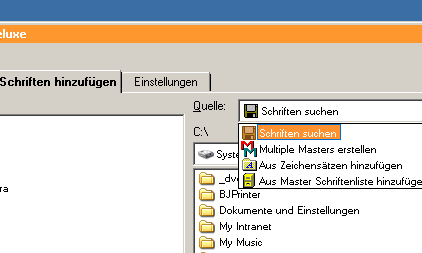
Abkürzungen oder: Welche Schrift soll ich nehmen?
Ich habe eine Auswahl an Minion-Schriften. Es gibt da:
SprMinion.bmap
Minion MM
Minion MM Expert
Bei anderen Schriften habe ich manchmal (also auch nicht immer! ...?) hinten stehen:
.bit
.suit
.scr
.mrf
MN
MS
BQ
MT
TT
CE
Das was vorne Steht, ist das immer der Hersteller (z. B. FF für FontFont)?
Aber dann steht da auch:
~
*
Was bedeuten diese Abkürzungen?
(Alles Ansicht Suitcase auf OS X 10.3)
.bit
.suit
.scr
.mrf
dürften Dateiendungen sein, was genau bin ich aber überfragt (ich gestalte unter windows). Lässt sich die Anzeige nicht umstellen in Suitecase?
FF ist tatsäclich der Hersteller (FontFont), weitere sind Adobe, Linotype, ITC und viele weitere.
MM bedeutet "Multiple Master", eine Schrifttechnologie, bei der der Anwender nicht nur festgelegte Schnitte zur Verfügung bekommt, sondern selbst in geregelten Bahnen "Zwischenschnitte" erstellen kann. Bei der Minion MM lässt sich z.B. das Gewicht und der Detailgrad der Zeichen stufenlos einstellen.
PRO verwendet Adobe (und andere Hersteller auch?) für ihre gut ausgebauten Opentype-Schriften.
Expert kommt aus der Zeit, als Schriften noch zu wenig Platz für alle Zeichen hatten. Sonderzeichen wurden in einen Expert-Schnitt ausgelagert, bei bedarf an so einem Zeichen musste man die Schrift wechseln um das Zeichen anzeigen zu können. Umständlich und mit Opentype Geschichte.
Bei CE bin ich mir nicht ganz sicher, meine aber es habe was mit osteuropäischem Zeichensatz zu tun...
SC ebenfalls ein "Relikt" aus Vor-Opentype-Zeiten. Smallcaps (Kapitälchen) sind Großbuchstaben in der Größe von Kleinbuchstaben. Wurden aus Platzmangel ebenfalls ausgelagert in eigene Schnitte.
Die anderen Endungen sagen mir auf die Schnelle nichts... Wahrscheinlich sind sie schrift- oder herstellerspezifisch...
SprMinion.bmap
Ist ’ne Bitmap-Schrift
Minion MM
Minion MM Expert
Expert ist ein spezieller Zeichenvorrat als Ergänzung zu den „normalen“ Buchstaben. MM steht für Multiple Master. Theoretisch könntest Du damit Fette, Buchstabenbreite etc. beeinflussen und einen neuen Schnitt generieren, Wie das aber geht, weiß ich auch nicht - und habe es auch noch nie gebraucht.
Bei anderen Schriften habe ich manchmal (also auch nicht immer! ...?) hinten stehen:
.bit
Keine Ahnung.
.suit
Ist ein Postscript-Zeichensatzkoffer.
.scr
.mrf
MN
Keine Ahnung.
MS
Könnte das für Microsoft stehen?
BQ
Steht für Berthold, also einem Schriftenhersteller.
MT
Noch nie gehört.
TT
True Type Font.
CE
Central European - also eine Schrift mit osteuropäischen Schriftzeichen.
Das was vorne Steht, ist das immer der Hersteller (z. B. FF für FontFont)?
Aber dann steht da auch:
~
*
Da hat es einfach nur den Namen zerstört - wahrscheinlich beim PC-Mac-Transfer.
MM bedeutet "Multiple Master", eine Schrifttechnologie, bei der der Anwender nicht nur festgelegte Schnitte zur Verfügung bekommt, sondern selbst in geregelten Bahnen "Zwischenschnitte" erstellen kann. Bei der Minion MM lässt sich z.B. das Gewicht und der Detailgrad der Zeichen stufenlos einstellen.
Wie geht das eigentlich?
Kann ich denn diese Bitmap-Schrift für den Druck verwenden? Oder ist das der Bitmap-Satz, einer PostScript-Schrift?
Gibt es Regeln, dass z. B. der Schrifthersteller immer seine Endung vorne hat und andere Dinge hinten stehen, oder ist das bunt-gemischt?
MM bedeutet "Multiple Master", eine Schrifttechnologie, bei der der Anwender nicht nur festgelegte Schnitte zur Verfügung bekommt, sondern selbst in geregelten Bahnen "Zwischenschnitte" erstellen kann. Bei der Minion MM lässt sich z.B. das Gewicht und der Detailgrad der Zeichen stufenlos einstellen.
Wie geht das eigentlich?
entweder über den ATM, wo man sich dann benutzerdefinierte schnitte erstellen lassen kann, oder z.b. über die multiple-master-palette in illustrator (zumindest ab version 10 dabei, wahrscheinlich auch schon früher), wo du live die parameter verändern kannst.
ob indesign, xpress und freehand das können, weiß ich nicht.
bisher einmal benutzt für einen speziellen Initial bei der Minion MM... Im Grunde eine nette Technologie, leider braucht man sehr viel Fachkompetenz um sie nutzen zu können. Die Entscheidung, welcher Schnitt z.B. für Mengensatz gut geeignet ist, möchte ich lieber dem Schriftgestalter überlassen. Nicht umsonst wird das ja zuvor ausgetestet, und ich bezweifle dass das bei den vielen MM-Stufen möglich ist. Vielleicht nehm ich die Sache aber auch viel zu ernst :lol:
MT dürfte für Monotype stehen.
Hier noch ein paar andere:
BQ Berthold Exclusiv
BT Bitstream
BV Blue Vinyl
CK Creating Keepsakes Schriftgießerei
DB Data Becker Schriftgießerei
DTC Digital Type Company
DTL Dutch Type Library
EF E+F (Elsner+Flake) Library
FB Font Bureau Schriftgießerei
GD Galapagos Design
ICG Image Club Graphics
ITC International Typeface Corporation
ITF International Typefounders
JSL Jeffrey S. Lee
LET Letraset
LH Linotype Hell
LHF Letterhead
LT Linotype Library
MS Microsoft
MT Monotype
SF Shy Fonts Schriftgießerei
STF Storm Type Foundry
URW URW++ Design & Development
WF Walden Fonts
Sonst kenne ich noch:
SC Small Caps = Kapitälchen
OsF Oldstyle Figures = Mediävalziffern
LF Lining Figures = Tabellenziffern
OCR Optical Character Recognition
ESQ Enhanced Screen Quality
XSF Excellent Screen Font
Pro OpenType-Zeichensatzdatei mit zusätzlichen typografischen Funktionen – beispielsweise die Unterstützung und Einbettung von Alternativzeichen wie Kapitälchen, Mediävalziffern, Ligaturen und Zierbuchstaben.
CE Central-European
DFR Deutsche Fraktur Layout
IPA Internationales Phonetisches Alphabet
Für was steht denn W1,
also z.B. Garamond (W1)